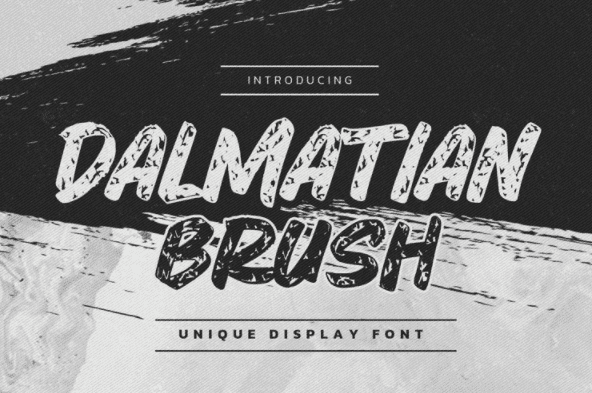
Название: Dalmatian Brush Font (2022)
Вот и наш новый шрифт Dalmatian Brush это уникальный шрифт, который пишется непринужденно и быстро. Это аутентичная кисть и стильный стиль.
Этот шрифт создан вручную с помощью кистей в Procreate. Этот шрифт отлично подходит для ваших творческих проектов, таких как водяной знак на фотографии, и идеально подходит для логотипов и брендинга, фотографии, приглашений, водяных знаков, рекламы, дизайна продуктов, канцелярских принадлежностей, свадебных дизайнов, этикеток, упаковки продуктов, специальных мероприятий или всего, что требует рукописного вкуса.
Это естественный рукописный шрифт. Этот шрифт ручной работы сделает ваш дизайн красивым и естественным. Он идеально подходит для любого дизайнерского проекта, как приглашение, логотип, обложка книги, ремесло или любые цели дизайна.
То есть Dalmatian Brush - это сильная характеристика более естественного вида для вашего текста с более современным видом для вашего текста.
Название: Dalmatian Brush Font (2022)
Вот и наш новый шрифт Dalmatian Brush это уникальный шрифт, который пишется непринужденно и быстро. Это аутентичная кисть и стильный стиль.
Этот шрифт создан вручную с помощью кистей в Procreate. Этот шрифт отлично подходит для ваших творческих проектов, таких как водяной знак на фотографии, и идеально подходит для логотипов и брендинга, фотографии, приглашений, водяных знаков, рекламы, дизайна продуктов, канцелярских принадлежностей, свадебных дизайнов, этикеток, упаковки продуктов, специальных мероприятий или всего, что требует рукописного вкуса.
Это естественный рукописный шрифт. Этот шрифт ручной работы сделает ваш дизайн красивым и естественным. Он идеально подходит для любого дизайнерского проекта, как приглашение, логотип, обложка книги, ремесло или любые цели дизайна.
То есть Dalmatian Brush - это сильная характеристика более естественного вида для вашего текста с более современным видом для вашего текста.